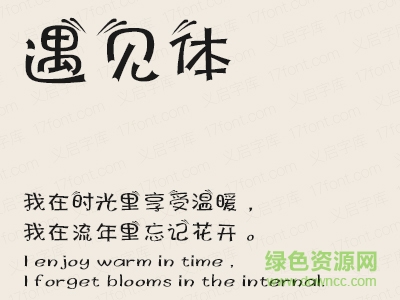
義啟遇見(jiàn)體字體
義啟遇見(jiàn)體是一款浪漫時(shí)尚風(fēng)格的藝術(shù)字體,遇見(jiàn)體筆畫(huà)圓潤(rùn),有特別的雙撇雙捺點(diǎn)綴效果,非常有新意,更多類似好看字體盡在綠色資源網(wǎng)!
義啟遇見(jiàn)體
義啟遇見(jiàn)體,于千萬(wàn)人之中遇見(jiàn)你,在時(shí)間無(wú)涯的荒野里,沒(méi)有早一步,沒(méi)有晚一步,剛巧趕上,沒(méi)有別的話可說(shuō),惟有輕輕地問(wèn)一聲:“噢,你也在這里嗎?”